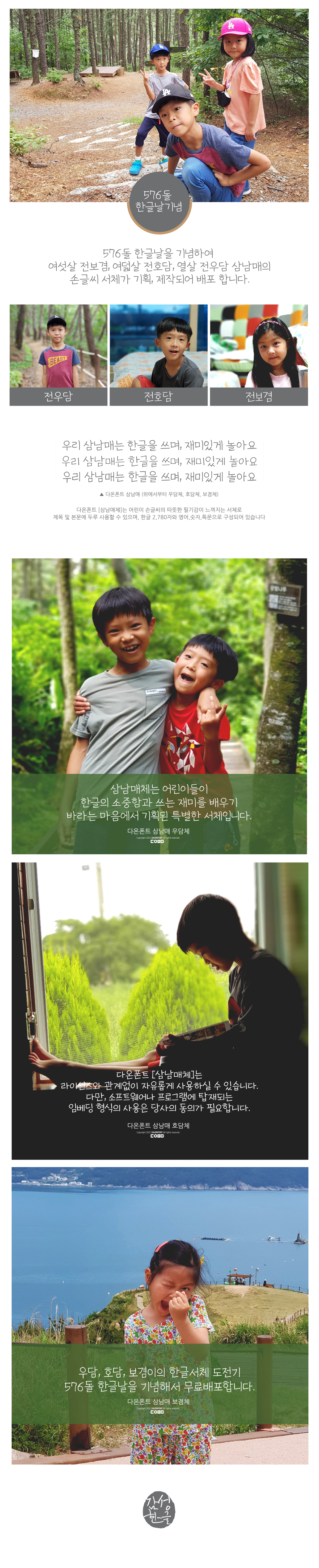
한글날 576돌 기념 '다온폰트 삼남매' 3종 무료배포
다온폰트에서는 576돌 한글날을 기념하여 [다온폰트 삼남매] 3종을 무료로 배포합니다.
다온폰트 삼남매는 손글씨로 참여한 삼남매의 이름인 우담, 호담, 보겸을 넣어 총 3종으로 구성되어 있습니다.
각 폰트의 구성은 한글 2,780자와 영어, 숫자, 특수문자로 구성되어 있습니다.